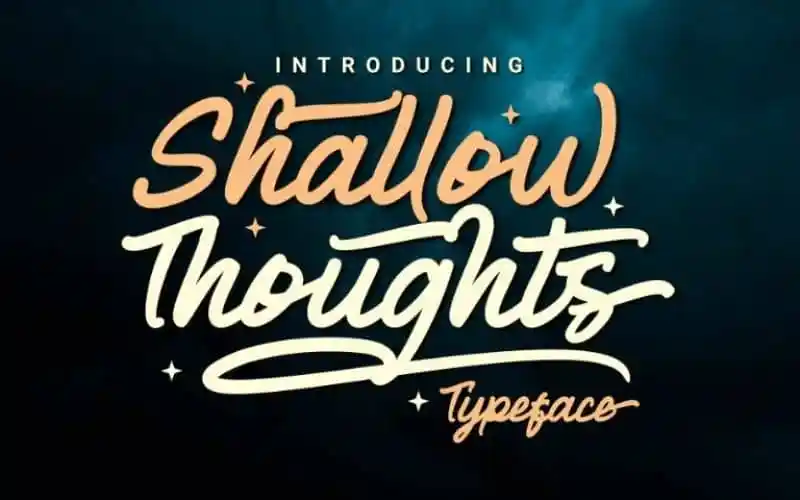
Shallow Thoughts Script Font – Download Grátis
Shallow Thoughts Script Font é uma fonte à mão livre moderna e única, criada pelo designer Toni Dzulham. Esta fonte traz a essência cool de uma escrita à mão, mas com um toque de modernidade que irá dar um toque especial ao seu design. Feita para aqueles que buscam tanto estilo quanto versatilidade, Shallow Thoughts oferece uma aparência simples e impressionante, compatível com todos os tipos de caracteres do alfabeto grego minúsculo a maiúsculo, números, símbolos, ligação entre letras e até mesmo com estilos alternativos. Com suporte para idiomas multilíngues, você pode usar esta fonte em qualquer design gráfico sem preocupações de legibilidade ou uniformidade. Uma boa escolha para quem quer adicionar um toque diferente e criativo ao seu trabalho.